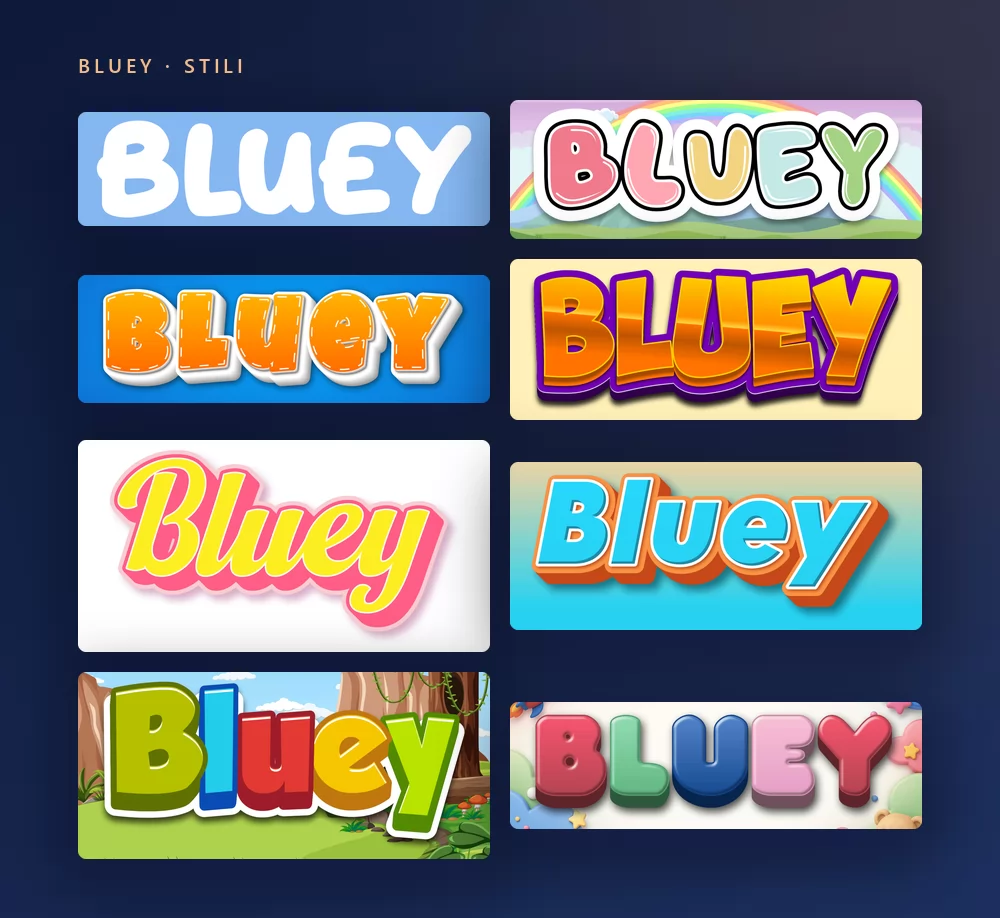
Informazioni sul font di Bluey
Bluey è una serie animata australiana per bambini in età prescolare, creata da Joe Brumm e prodotta da Ludo Studio a Brisbane. È andata in onda per la prima volta su ABC Kids nel 2018 e ha fatto il giro del mondo con BBC Studios e Disney+. Segue Bluey, una cucciola di Blue Heeler di sei anni, la sorellina Bingo e i genitori Bandit e Chilli, in giochi di fantasia che finiscono sempre per lasciare una lezione di vita anche agli adulti che guardano.
Il logo della serie è un lettering su misura: maiuscole spesse, tonde, saltellanti, disegnate per il programma e mai pubblicate come carattere. Il font usato per tutto il resto, nel cartello del titolo, nei titoli di coda e sul sito ufficiale, è Hello Headline, disegnato da Veneta Rangelova e pubblicato da DearType. Quando nel 2023 è arrivato Bluey: The Videogame, anche "The Videogame" sotto il logo era composto in Hello Headline. È un font commerciale.
Per font gratuiti dall'aspetto simile, i siti posizionati su questa ricerca indicano tutti gli stessi tre: Blue Custard di rockcake, e Lovely Bubbles e Magical Markers di Darrell Flood. Heyam di FG Studios è l'altra corrispondenza commerciale vicina.
Come creare un testo Bluey
Passo 1. Scrivi il nome
Apri il generatore e sostituisci il testo di esempio con il tuo: il nome di un bambino, "Buon compleanno", un'etichetta per la classe. Le lettere si ridisegnano mentre scrivi. Lo stile mette tutto in maiuscolo da solo, come il logo.
Passo 2. Scegli uno stile
Il classico sono le maiuscole bianche tonde e spesse su azzurro cielo. La scheda Stili permette di cambiare separatamente riempimento, contorno e ombra, così tieni le lettere saltellanti e porti i colori altrove: arancione per una festa di Bingo, un rosa pallido, un arcobaleno.
Passo 3. Scegli il formato
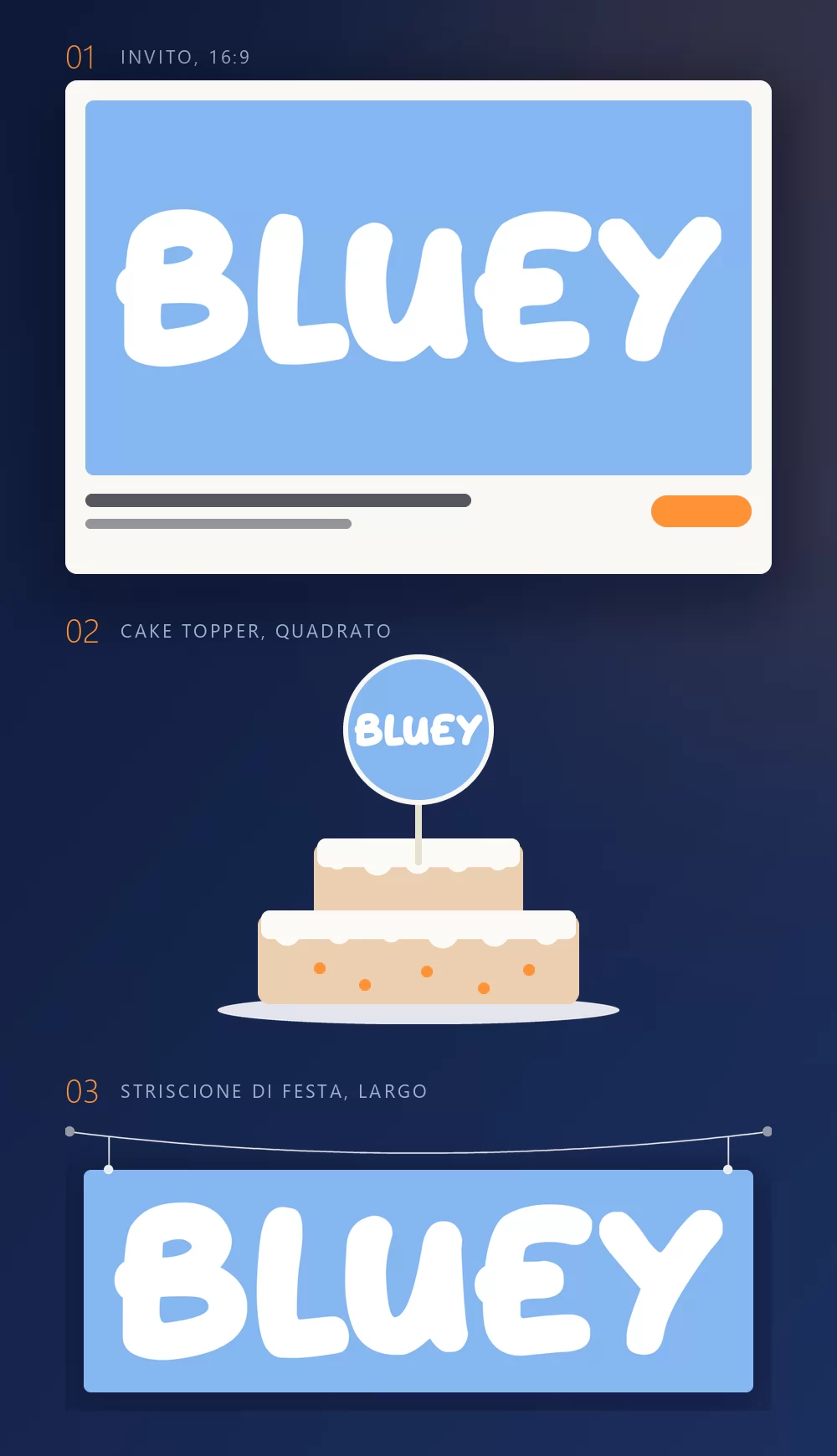
Imposta il formato prima di esportare e dopo non dovrai ritagliare niente. Un 16:9 per un invito, un quadrato per un cake topper o uno stecchino da cupcake, una striscia larga per uno striscione lungo la parete. Le tre simulazioni qui sopra sono ciò che diventano quei formati una volta stampati.
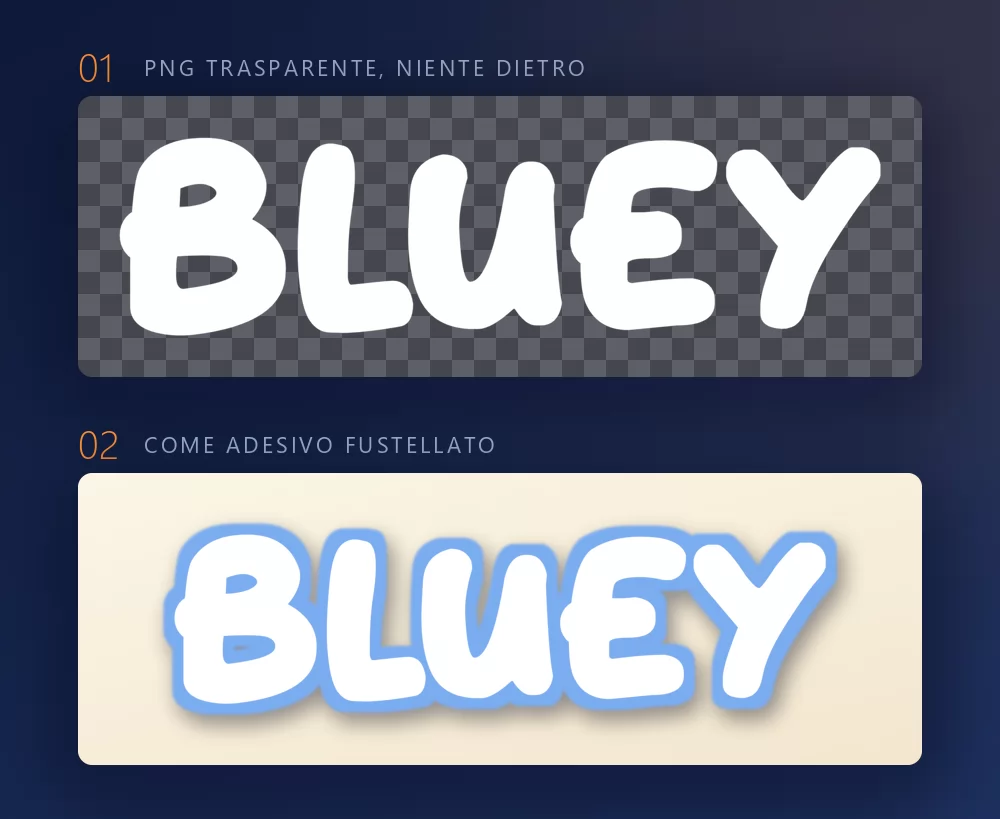
Nella scheda Scarica, prendi il PNG trasparente se vuoi mettere il nome sul tuo progetto. È l'opzione che quasi tutti si perdono, e per gli stampabili di una festa è quella che conta: la tua carta, il nome sopra, nessun riquadro blu intorno. È anche ciò che serve a un plotter da taglio per un adesivo fustellato o un topper: la forma delle lettere è la forma del taglio.
I nomi lunghi riempiono subito la larghezza
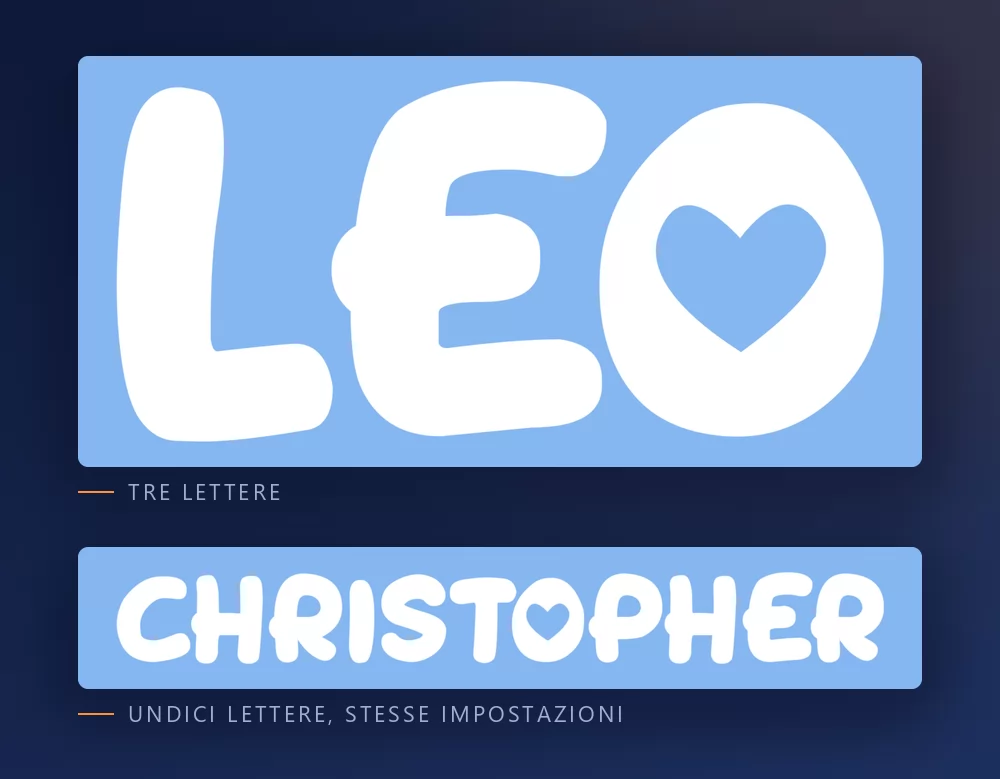
Più lettere ci sono, più si stringono. La spaziatura dei caratteri è un cursore della scheda Testo: aprila un po' e un nome lungo smette di sembrare schiacciato. La stessa scheda ha zoom, interlinea, curva e rotazione.
Lo stile Bluey o lo stile stanza dei giochi
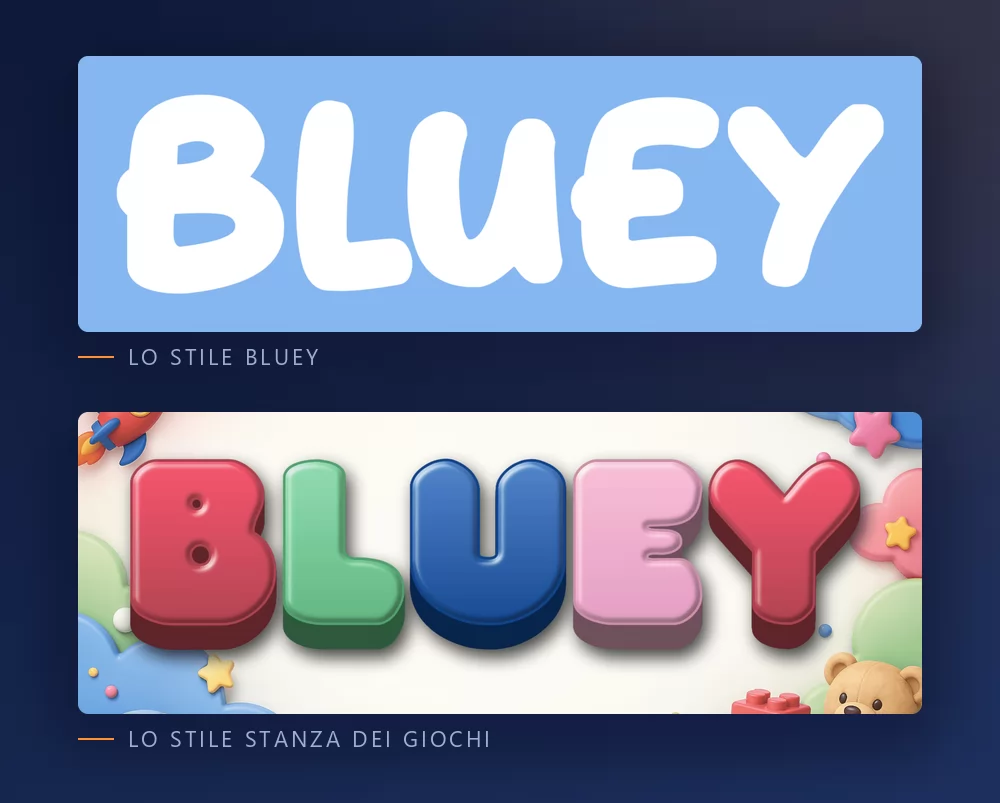
Lo stile Bluey è il logo stesso: bianco, spesso, tondo, un po' saltellante, su quell'azzurro cielo. È quello che quasi tutti hanno in mente, ed è quello che serve a un compleanno Bluey.
Lo stile stanza dei giochi sono lettere di plastica arrotondata in colori pastello, con giocattoli sparsi intorno. Non porta nessun marchio della serie, e questo lo rende la scelta migliore per la parete di una cameretta o un primo compleanno senza tema. Il generatore di lettere da stanza dei giochi lo ha tra le impostazioni.
Quale font, se vuoi installarne uno
Il logo in sé non è un font. È un lettering su misura, quindi qualsiasi file chiamato "font Bluey" è la ricostruzione di qualcuno.
Hello Headline è la vera risposta per il resto della serie. È un font commerciale di DearType, che si compra e si scarica dalla fonderia. Se vuoi esattamente l'aspetto del cartello del titolo e dei titoli di coda, è questo.
Blue Custard, di rockcake, è il font gratuito che più si avvicina alle maiuscole saltellanti del logo. È su DaFont come donationware: libero da usare, con una mancia gradita per l'autore.
Lovely Bubbles e Magical Markers, entrambi di Darrell Flood, sono gli altri due che ogni lista riporta. Lovely Bubbles è indicato come gratuito per uso personale, Magical Markers come donationware, entrambi su DaFont.
Per lavori con clienti, dove la licenza deve essere pulita, le opzioni oneste sono i font tondi a licenza aperta di Google Fonts: Fredoka, il più vicino nello spirito, con un'intera gamma di pesi, Baloo 2 e Sniglet. Nessuno è un font di Bluey. Tutti e tre danno l'aspetto tondo e amichevole con una licenza che nessuno può contestare, e sono disponibili dentro Canva.
Cosa ci fa davvero la gente
Le pagine di download elencano gli "usi migliori" e coincidono con quello che si fa davvero: inviti di compleanno, topper per torte e cupcake, striscioni lungo una parete, targhette con il nome per una festa, una maglietta per il festeggiato, etichette per la classe e cartelli di benvenuto. Quasi tutto si stampa, e quasi tutto funziona meglio con il PNG trasparente che con un font installato, perché l'aspetto sta nelle lettere bianche su quell'esatto azzurro cielo, e un file di font ti dà i contorni e nient'altro.
Perché il mio testo sembra sbagliato accanto al logo vero? Di solito è l'azzurro, non il font. Il logo sta su un azzurro cielo chiaro, leggermente grigio. Su un blu elettrico acceso, o con una sfumatura, smette di leggersi come Bluey.